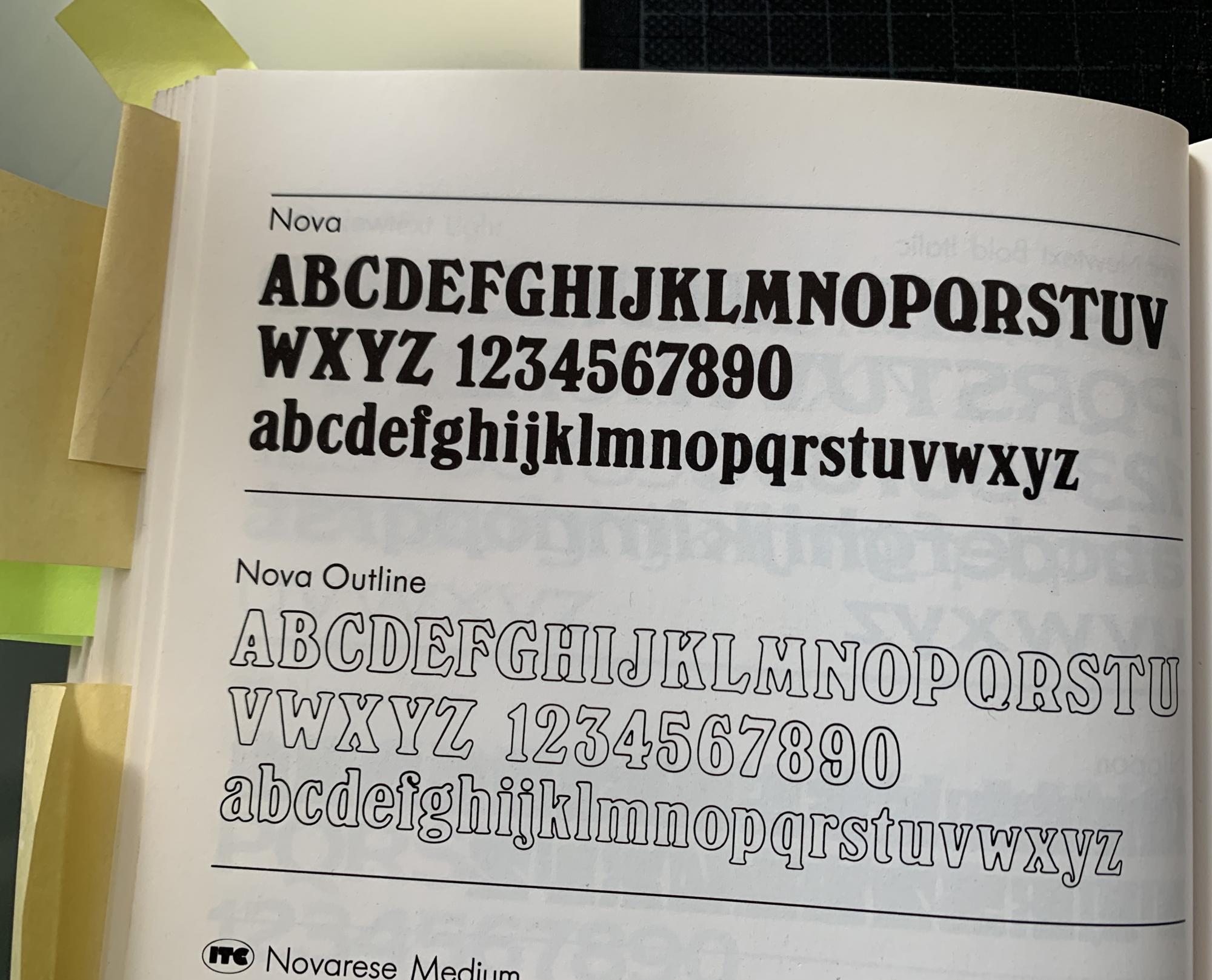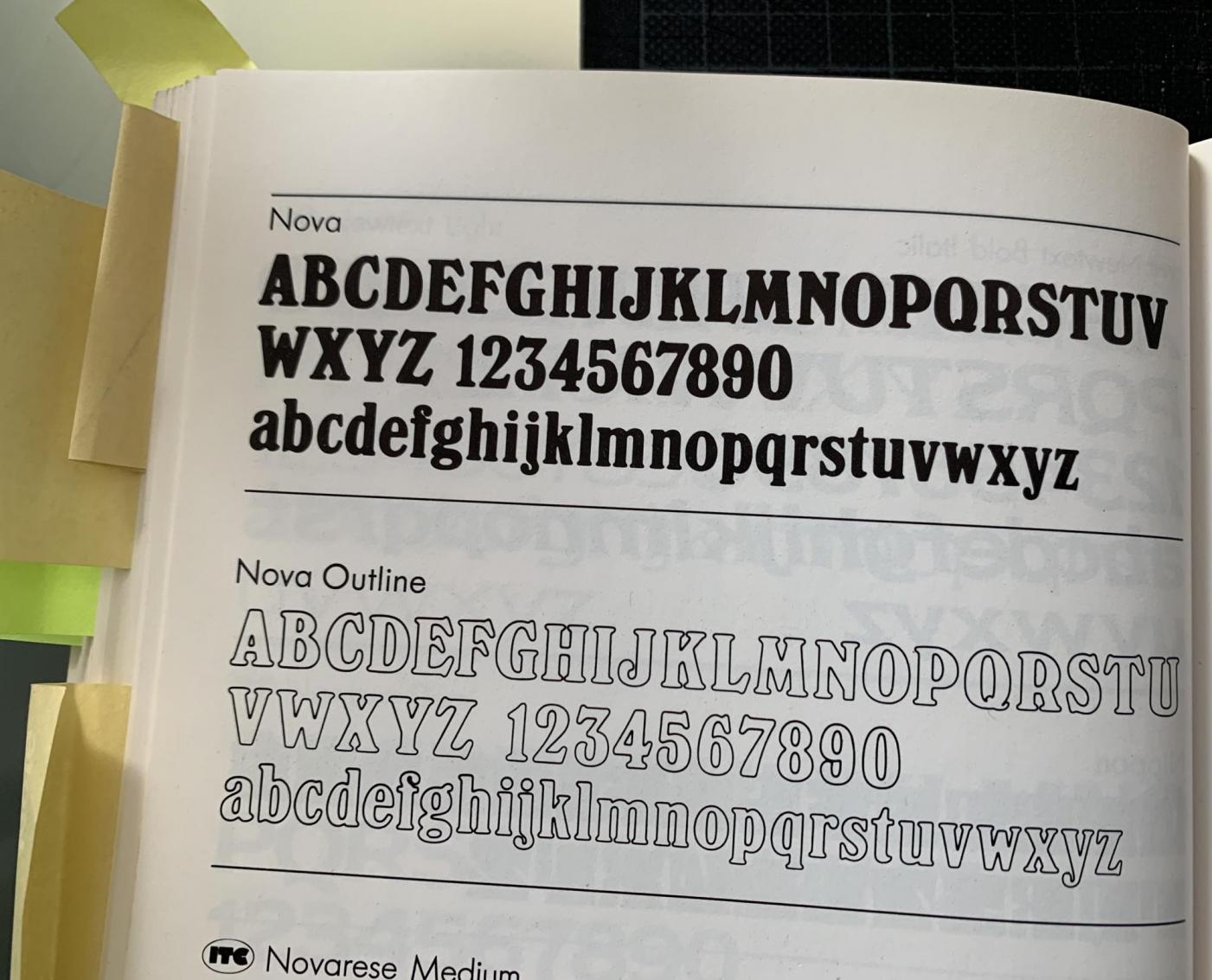
Gibt es die Schrift "NOVA" digital?
Die Zeitschrift "essen & trinken" hat in den 70er Jahren die Schrift "Nova" verwendet. Zumindest konnte ich das anhand alter Schriftbücher herausfinden. Leider gibt es unter dem Suchbegriff "Nova" im Netz komplett andere Schriften. Sollte es die Nova noch geben, ist sie vermutlich umbenannt worden. Weiß eine/r von Euch Rat? Das würde mich freuen. Vielen Dank
Erinnert mich an die Nachschlagewerke von CorelDraw … dann vermute ich aber einen anderen Namen als Original. Eine "Windsor Condensed" käme aber schon gut hin, gibt ja leider viele Versionen.
Was für ein Schriftmusterbuch ist das denn? Welcher oder welche Hersteller werden da vertreten?
Die "Nova" hatte ich im Buch "Alphabete/Alphabets" von Erhardt D. Stiebner aus der Reihe "novum press" des Bruckmann Verlages gefunden, Ausgabe von 1984.
Ja, hatte ich auch erst gehofft, allerdings ist dort zum Beispiel das kleine "o" anders. Bei den Großbuchstaben gibt es große Ähnlichkeiten, das stimmt.